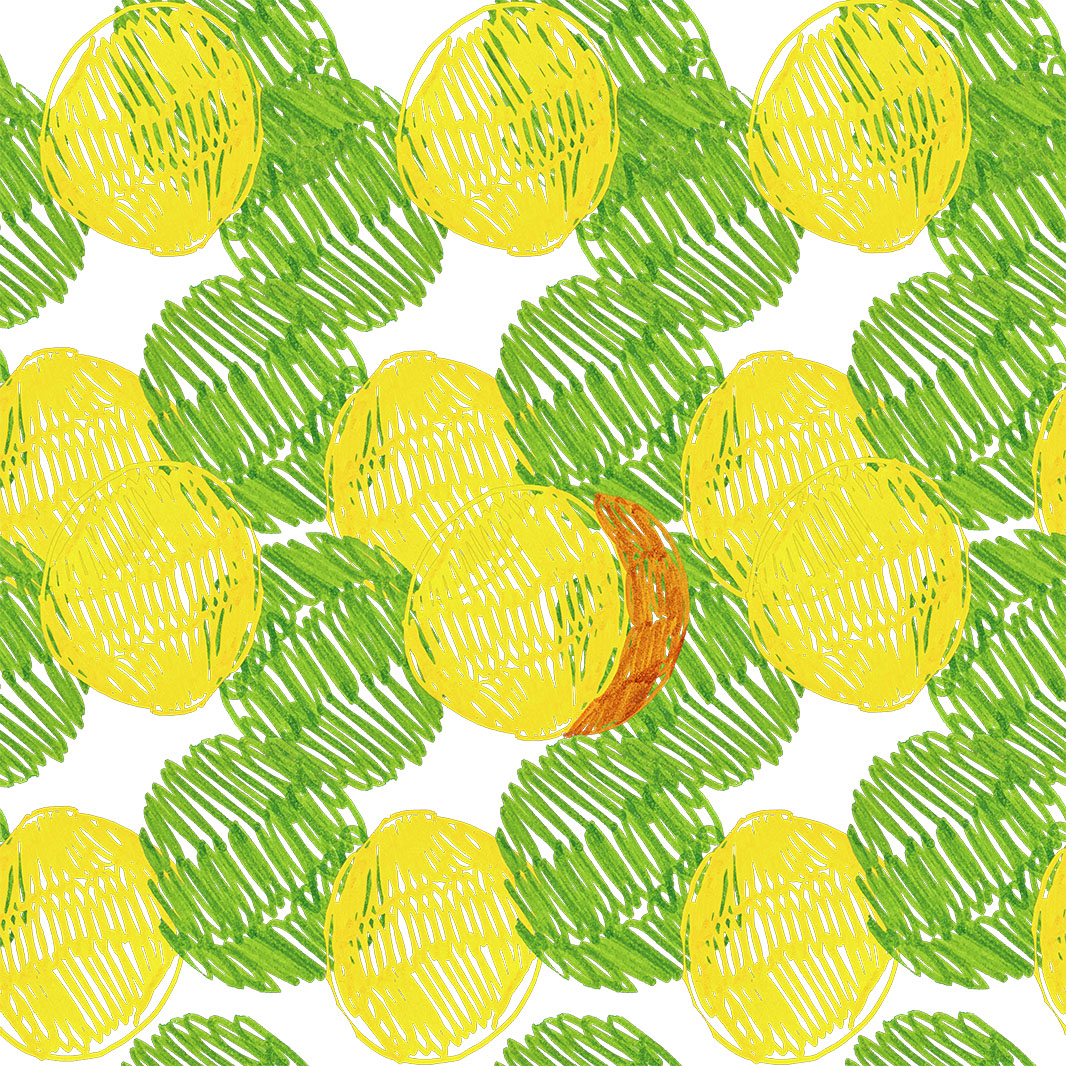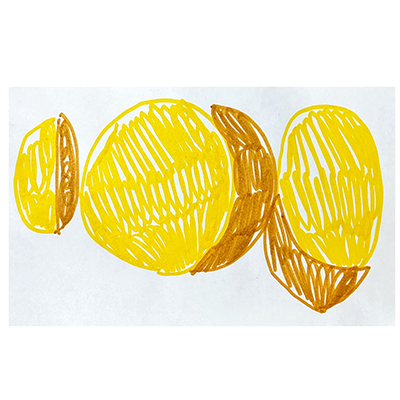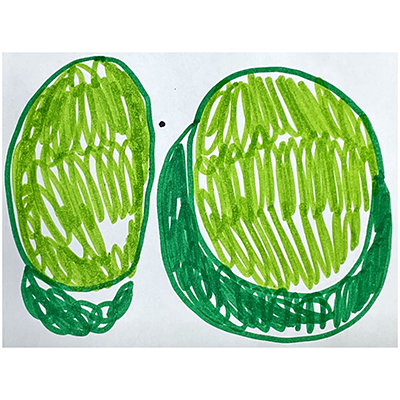
べじドッド
ころころ、野菜かくれんぼ。
アーティストさんにじゃがいもときゅうりを描いてもらった絵の線の動きの楽しさを残しながらデザインした(Sana)
毎年どんな学生さんが来るのか期待と不安でそわそわしているアーティスト。絵の依頼をされて、とてもうれしそうな表情が印象的でした。次から次へハイスピードで描かれる野菜が、持ち味そのままにかわいらしいデザインになりました。(くるるえびす)